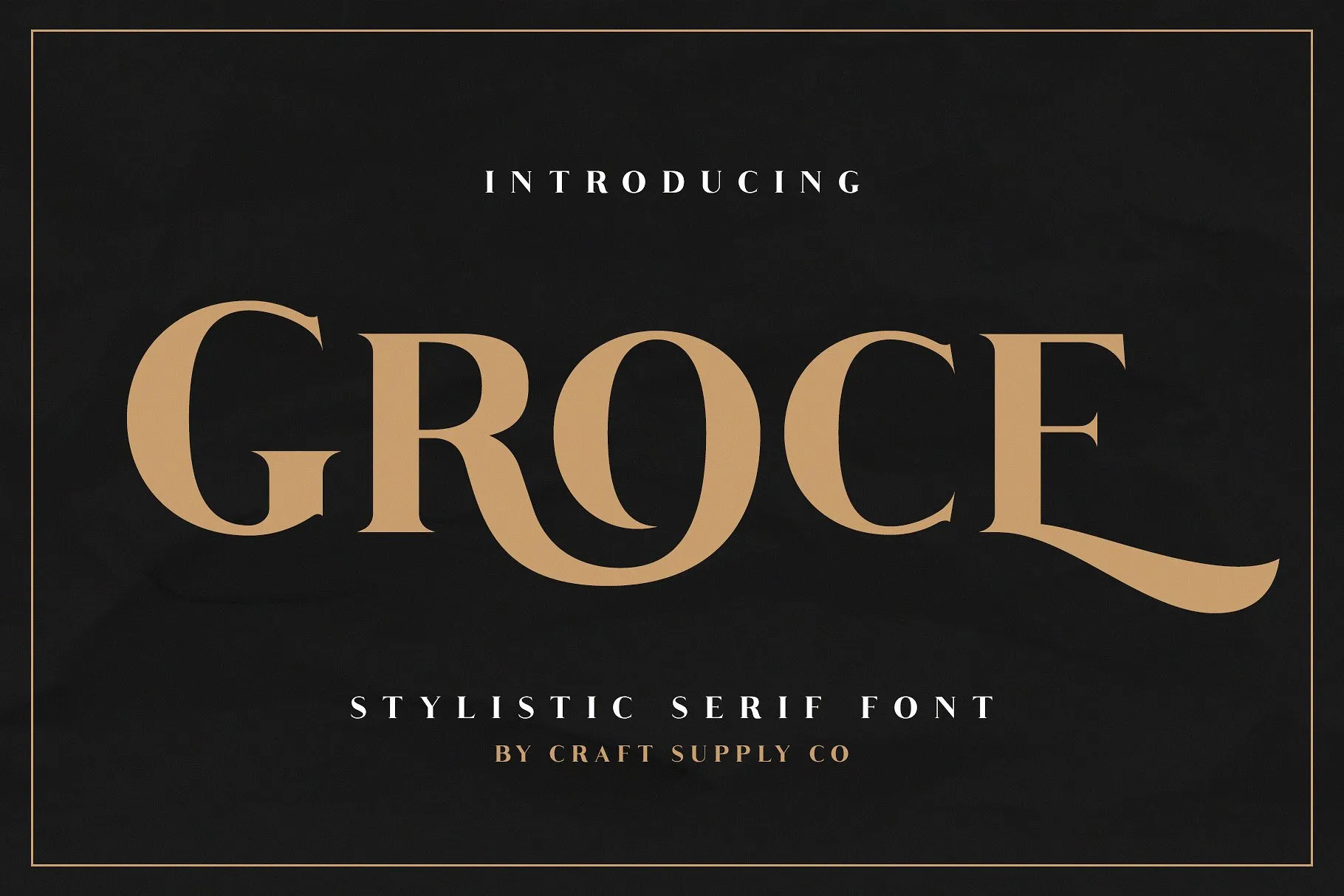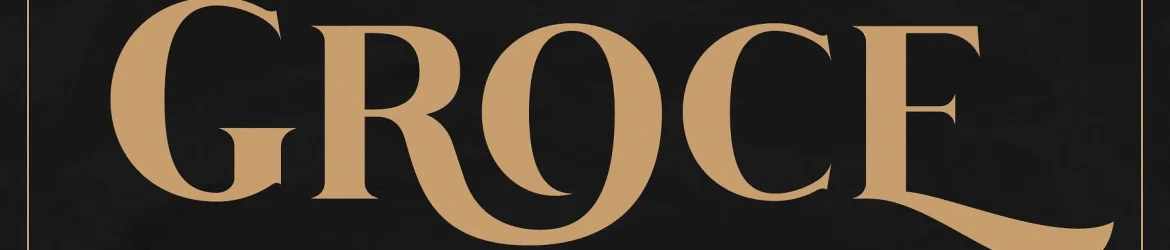
Groce Stylistic Serif Font – Download Grátis
A Groce Font é uma elegante serif que combina sofisticação com versatilidade. Introduzida no mercado, a Groce Stylistic Serif representa não apenas uma ferramenta de escrita profissional, mas também um instrumento criativo para expressar talentos visuais. Ela foi cuidadosamente concebida por zziplex para oferecer inúmeras possibilidades, especialmente para projetos alternativos e modernos. Perfeita para aplicação em elementos decorativos como capas de livros ou até mesmo a criação de materiais promocionais como cartazes e embalagens, a Groce Stylistic Serif é uma escolha ideal para quem valoriza estilo sofisticado em seus projetos. Combinando elegância com um toque moderno, ela se destaca como fonte perfeita para criar um visual único e memorável em qualquer tipo de projeto gráfico.